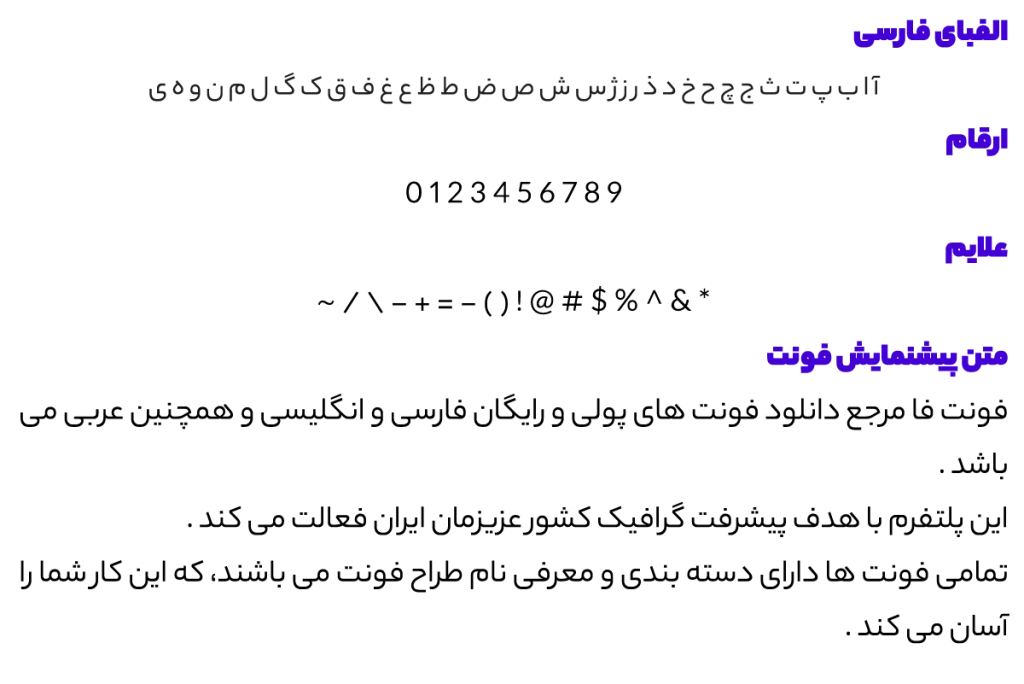
پیشنمایش فونت یکان بخ
فونت فارسی یکان بخ - Yekan Bakh
توضیحات و معرفی فونت یکان بخ
فونت فارسی یکان بخ ( Yekan Bakh ) از مجموعه فونت های آزاد می باشد، همچنین نوع فونت طراحی وب و عنوان و متن می باشد.
فونت فوق العاده زیبای معرفی شده توسط رضا بختیاری فرد در سال 1394 طراحی و ساخته شده است.
همچنین فونت یکان بخ در 9 وزن نازک و سبک و معمولی و نیمه پر رنگ و فوق العاده سنگین و فوق العاده پررنگ و نسخه وریبل است.
در لیست زیر می توانید وزن های این فونت فوق العاده زیبا را ببینید.
1. Yekan Bakh Thin
2. Yekan Bakh Light
3. Yekan Bakh Regular
4. Yekan Bakh DemiBold
5. Yekan Bakh Bold
6. Yekan Bakh ExtraBlack
7. Yekan Bakh Black
8. Yekan Bakh ExtraBold
9. Yekan Bakh Variable
یکان‌بخ از کجا پدیدار شد؟
این فونت زیبا دستاورد طراحی و توسعه فونت یکان محبوب و پر طرفدار می باشد.
تاپ فیس یکان توسط مسعود سپهر در سال 1359 هجری شمسی طراحی شده بود.
آقای بختیاری فرد در سایت 1395 این فونت را بازطراحی کرد و در 9 وزن و نسخه های متفاوت روانه بازار نمود.
برای زبان انگلیسی یا لاتین این فونت از فونت اوپن سورس Kanit استفاده شده است.
رضا بختیاری فرد در مورد فونت یکان بخ  اینگونه میگوید:
در طراحی یکان‌بخ از فرم‌های هندسی کمک گرفتم، اما خود را به استفاده از آن فرم‌ها محدود نکردم و کاراکترها به‌طور کامل با فرم‌های هندسی منطبق نیستند. دلیل این کار حفظ خوانایی و در نظر گرفتن خطای دید در طراحی بود. هم‌چنین فرم‌های هندسی باعث می‌شوند حروف شخصیتی سرد و ماشینی به‌خود بگیرند؛ به‌ویژه در رسم‌الخط عربی که چندان با فرم‌های هندسی میانه‌ای ندارند.
زمانی طول نکشید که ای فونت در بین طراحان رابط کاربر سایت یا اپلیکشین اندروید محبوب شد.
و خیلی از سایت های پربازدید مثل موزیکفا، دیجی کالا و بسیاری دیگر از سایتهای خوب ایرانی استفاده کرده اند.
در ادامه همین پست می توانید نمونه شعر معروف وطن نوشته شده توسط فونت یکان بخ را ببنیید.
دمو فونت یکان بخ
مقایسه فونت یکان بخ و بی یکان
در این تصویر می توانید دو فونت ذکر شده را باهم مقایسه کنید و تفاوت های این دو فونت را ببینید.
مقایسه فونت یکان بخ و بی یکان